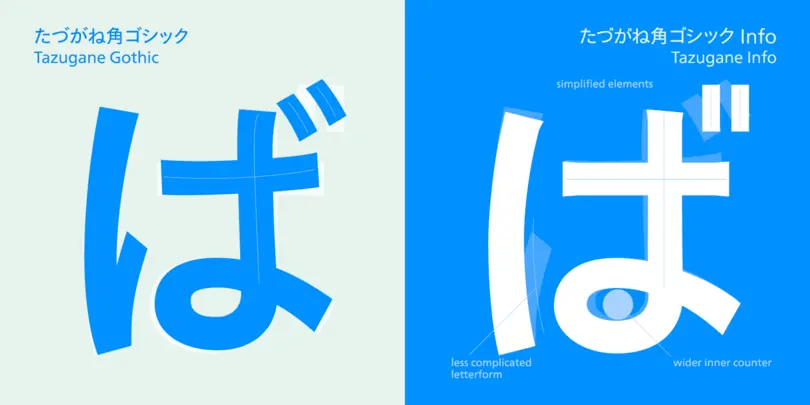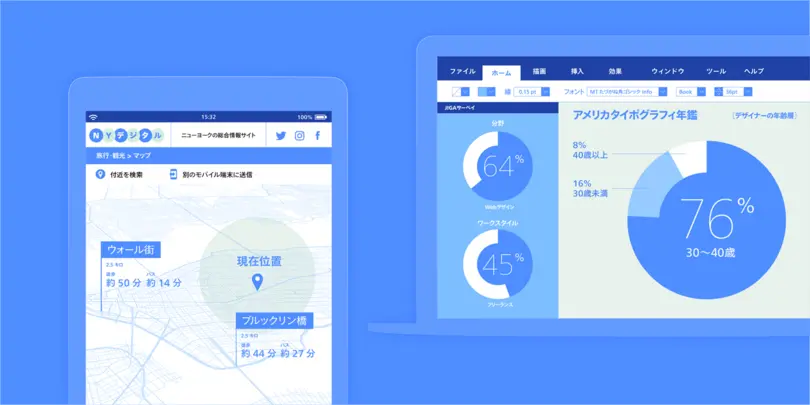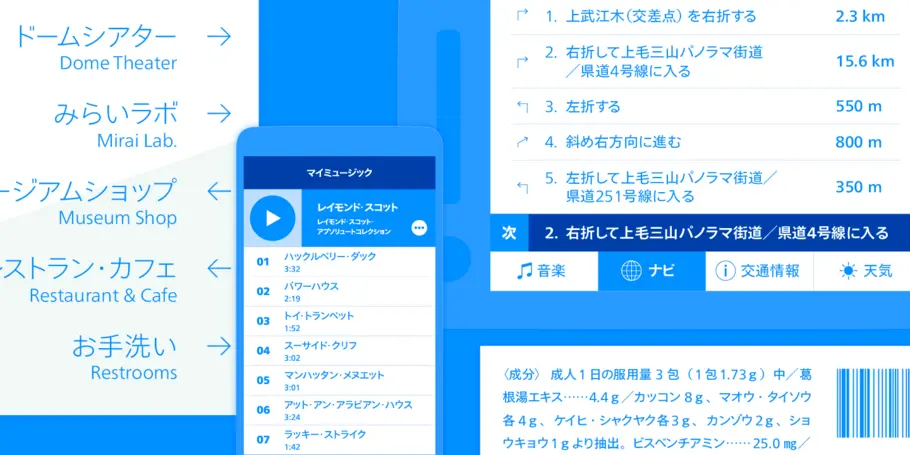
たづがね角ゴシック Info
Tazugane info
たづがね角ゴシック Infoは、ヨコ組みに特化した仮名を備えています。たづがね角ゴシックの漢字・欧文部分はそのままに、ヨコ方向に組まれたテキストの安定感を考えて整理されたデザインは、情報を端的に伝える場面で力を発揮します。
「見やすく読みやすく」、その別の形
特にカタカナ部分は落ち着いた印象と水平のラインを意識したつくりで、製品名や外来語などカタカナが多く使われる昨今の環境になじむデザインです。たづがね角ゴシックの設計思想は引き継ぎつつ、より機能的な側面を強調して設計された結果、たづがね角ゴシックに比べてフトコロがやや大きめでシンプルな字形となっています。濁点部分に関しては水平・垂直方向の線のみで整理されており、かっちりとした機能的な印象を演出します。
Tazugane info
サイン、書籍、WEBなど、現在のメディアに対応し、見出し用、本文用それぞれの用途を考えて設計。他の欧文書体とも組み合わせ自由なウェイトバリエーションを用意しています。タブレット端末などのモバイルデバイス、コンピューターディスプレイ、車載用ディスプレイ、デジタルサイネージなどでの用途を想定し、より簡潔で幾何学的な形に仕上がっています。
Tazugane info
誰でも使いやすく。
読みやすさで定評のあるNeue Frutigerを英数字に採用し、英数字のサイズ・位置を、あらかじめ日本語にあわせて最適化しました。
誰でもキレイに詰め組みできるように豊富なペアカーニングが設計されています。
今までの仮名書体はヨコ組をした際に字間にバラツキが起きやすく、それを解決したいと思いました。今のモニター・ディスプレイや情報システムはヨコ組での表示が基本です。そこで、『たづがね角ゴシック』の設計思想を引き継ぎながらも、デジタル環境でブランドのメッセージがより明瞭に伝わる『たづがね 角ゴシック Info』を開発しました
10ウェイトで自在に。
「たづがね 角ゴシック Info」は「たづがね角ゴシック」と同じく10ウェイトで展開し、今回新たにデザインされた仮名のほか、「たづがね角ゴシック」の漢字と、和文に合わせて調整されたNeue Frutigerも搭載しています。和欧混植もスムーズで、デジタル・非デジタル環境を問わず、ブランディングに最適な書体です。
欧文書体との組み合わせ
「たづがね 角ゴシック Info」はNeue Frutigerのほか、DIN® NextFF Meta®Univers® NextNeue Helvetica® Nowなどとも相性のよい書体です。
フォント名の由来:タンチョウに代表される鶴は、古くから東アジアにおいてその気品ある佇まいや優雅に飛ぶ姿から瑞鳥とされ、文学や芸術品のモチーフとして多用されて親しまれてきました。日本では「鶴は千年、亀は万年」と言われるように長寿の象徴とされています。鶴は『万葉集』の歌にもよく詠まれており、【たづがね】という言葉は、この【鶴】を意味します。鶴の長寿にあやかり、末永く使われていくことを祈願して『たづがね角ゴシック』と名付けました。
現代のデザイナーのニーズに応えるために生まれたたづがね角ゴシックは、ゴシック体のDNAだけでなくその品位も受け継いでいます。